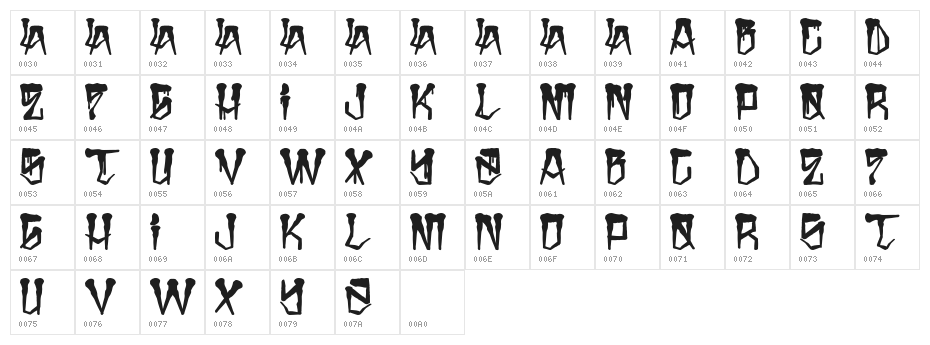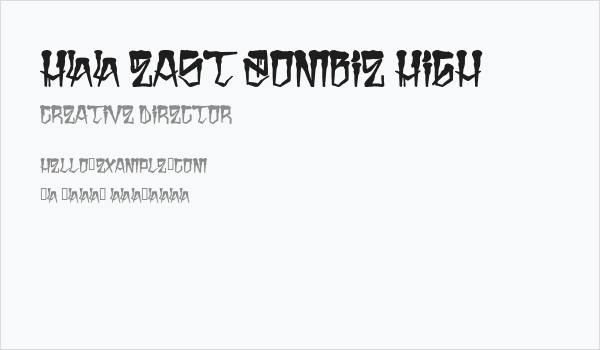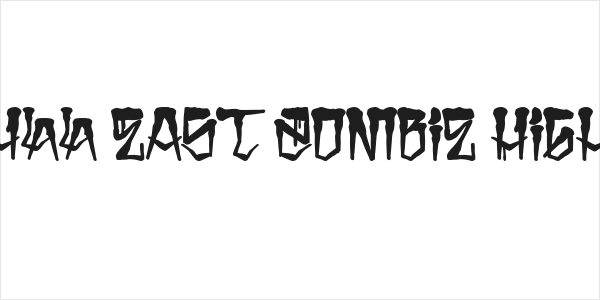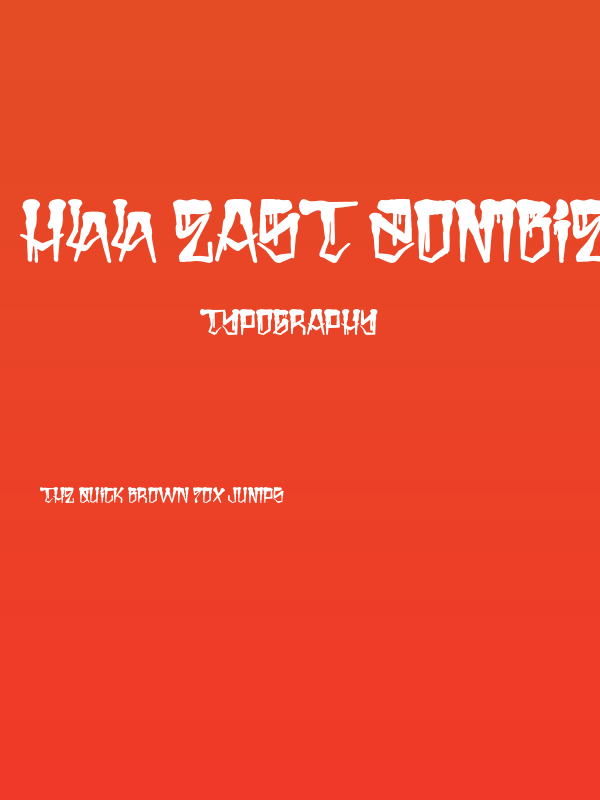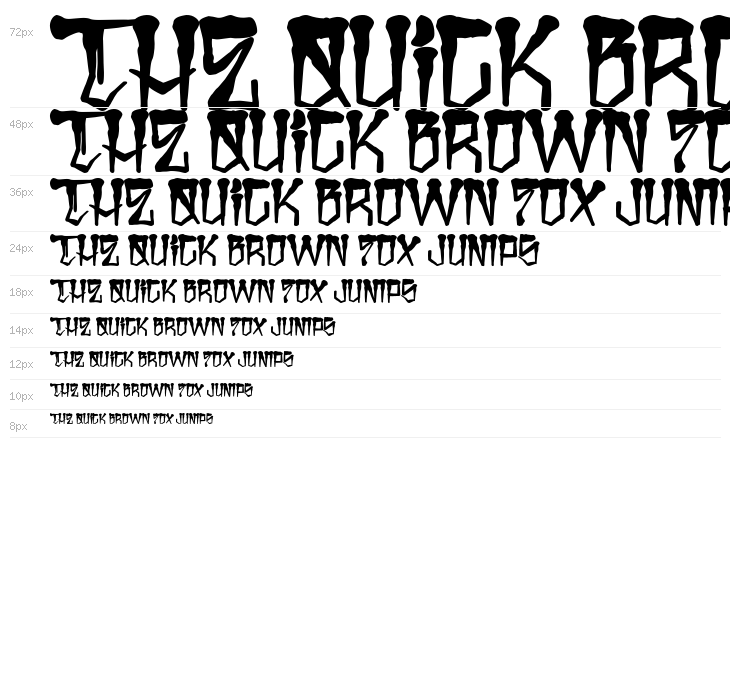
H74 East Zombie High Font
| Caso d'uso | Headlines, Posters, Logos |
| Progetti proposti | Ideal for Halloween-themed designs, horror movie posters, spooky event invitations, and any project requiring a dramatic, eerie aesthetic. |